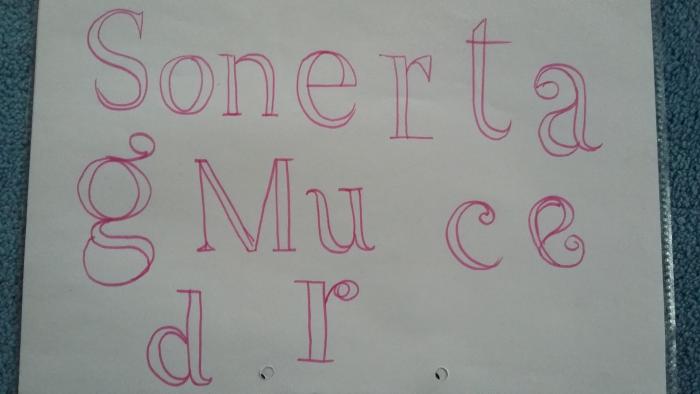
Suche Sonerta(?)
ich bin vor längerer Zeit über eine elegante und etwas spezielle Serifenschrift gestolpert, deren Adresse ich mir dummerweise nicht gespeichert habe. Ich bin mir ziemlich sicher, dass sie Sonerta oder ähnlich hieß und ich finde sie über Google nicht.
Ich suche nicht Sonera, die klingt zwar so, ist aber was ganz anderes.
Die Schrift war kommerziell und nicht auf den typischen Sammelseiten, sondern beim Autor (dessen Namen ich auch nicht mehr weiß) direkt zu kaufen. Vielleicht weiß ja jemand welche ich meine? Sie geht mir nicht mehr aus dem Kopf...
Sie geht mir nicht mehr aus dem Kopf...
Dann gelingt es Dir vielleicht die von Dir gesuchte Schrift noch etwas genauer zu beschreiben? :-? Auch »spezielle« Serifenschriften gibt es viele.
Die Narziss kommt dem auf jedenfalls sehr nahe, Vielen Dank dafür schonmal!
Ich hab die Schrift damals auf der Seite des Autors gefunden, ist eigentlich wahrscheinlich, dass es die auch bei myfonts gibt..